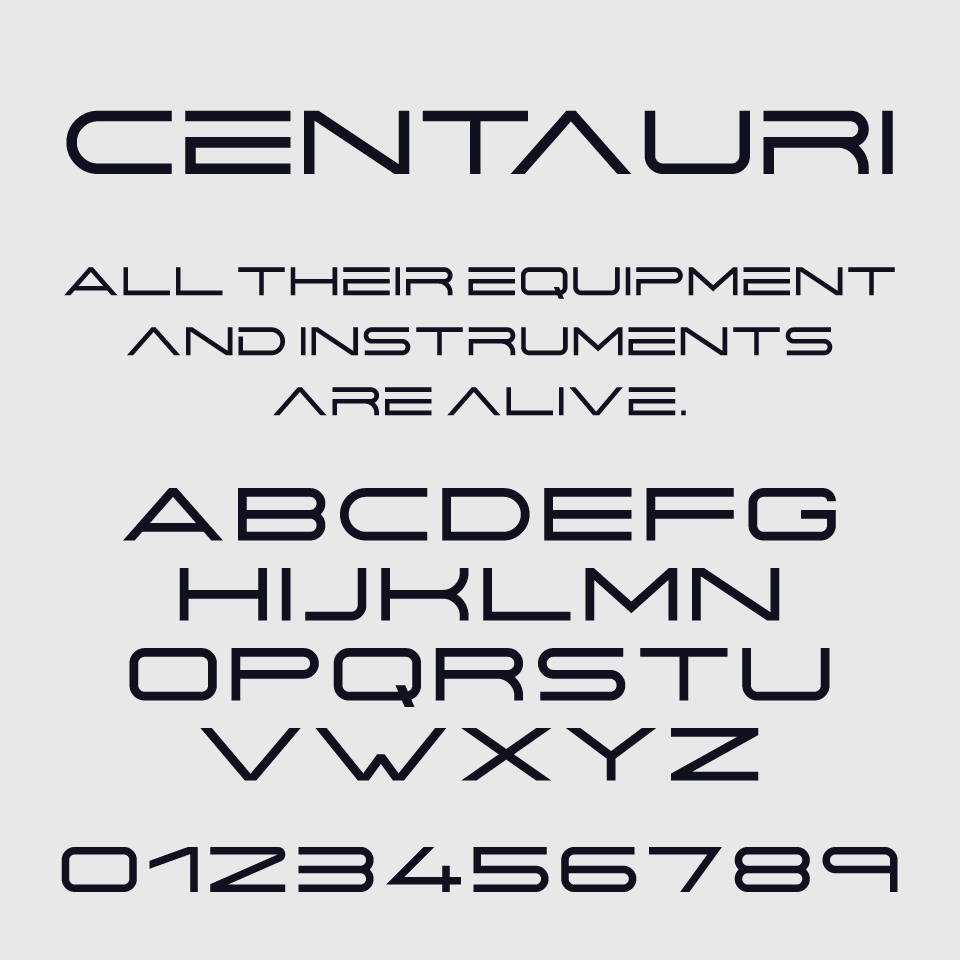
Centauriフォントは、近未来感を前面に打ち出したシャープなデザインのサンセリフ体です。
直線と丸みが組み合わさった幾何学的な文字構造が特徴で、まるで宇宙船のパネルに刻まれたようなサイバー感があります。角ばったディテールと細身のプロポーションが、洗練された雰囲気を生み出しています。
近未来感・SF映画のタイトルやハイテク系のブランディング、スタートアップ系のデザインなどにぴったりなフォントです。無駄な装飾を省いたミニマルな表情ながらも、どこか非現実的で夢のある印象を持たせるフォントです。